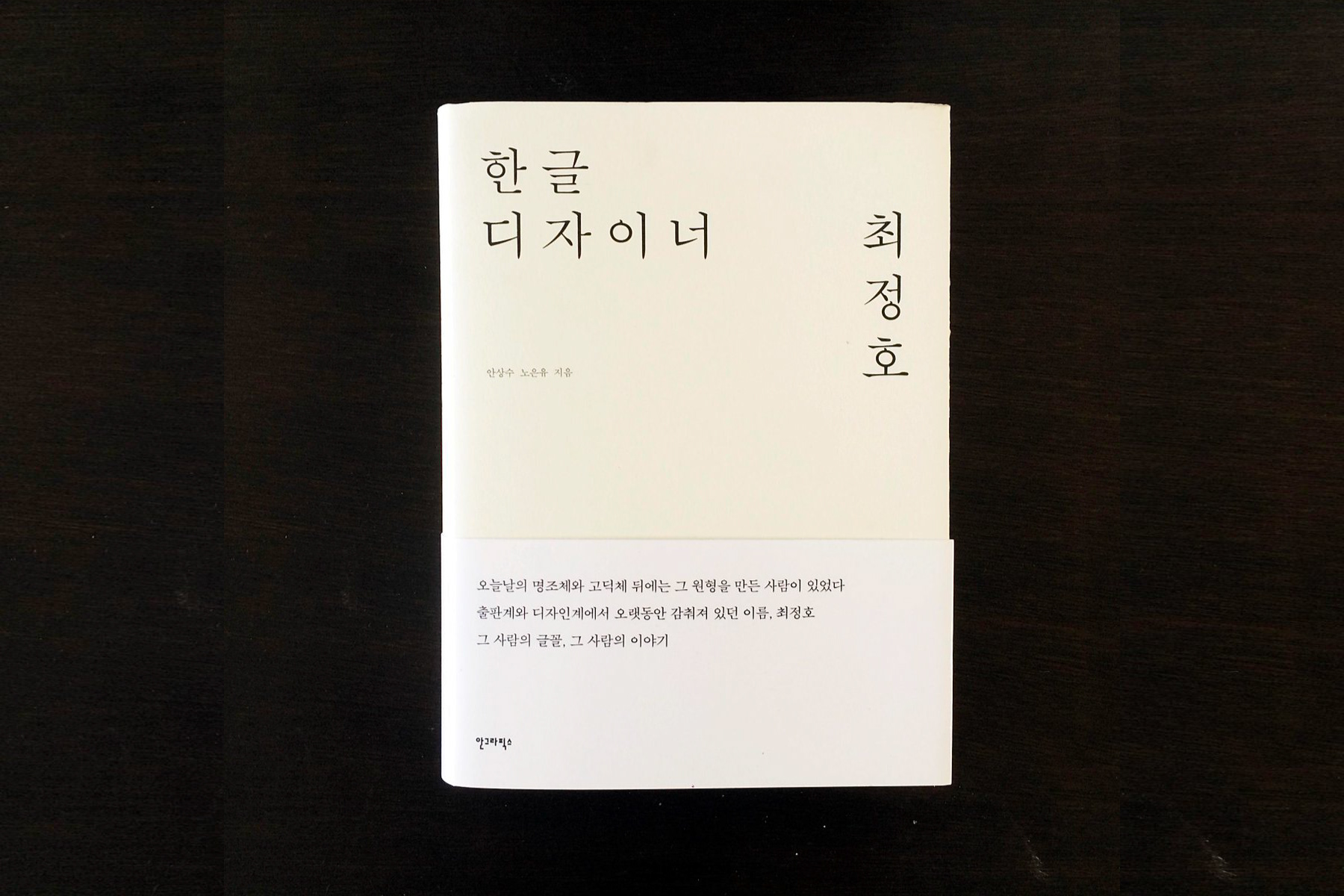
한글 디자이너 최정호​​​​​​​
Choi Jeong-ho’s Hangul Type Design, 2014
오늘날의 명조체와 고딕체의 원형을 설계한 1세대 한글디자이너 최정호 연구
Publication on Korea’s first generation Hangul type designer Choi Jeong-ho, responsible for the original designs of Myeongjo and Gothic.
글꼴에만 평생을 바친 최정호의 삶과 작업을 소개한 책이다.
먼저 ‘최정호의 삶’에서는 그의 삶을 하나하나 추적해 그를 기억하는 여러 사람의 목소리로 되돌아본다. 다음으로 ‘최정호의 한글꼴’에서 노은유의 박사논문을 바탕으로 최정호가 한국과 일본을 오가며 디자인한 수많은 글꼴을 체계적이고 논리적으로 분석했다. 또한 오늘날 명조체와 고딕체 계열 글꼴과 최정호가 디자인한 글꼴이 어떻게 이어져 왔는지 그 계보를 그렸다. 책의 마지막에는 최정호의 기고글, 작업 사진은 물론 그동안 공개된 적이 없는 글꼴의 원도(原圖)를 생생하게 보여주었다.
(207쪽 발췌) “글자란 사상이나 뜻을 전하는 도구이다. 특별한 조건이 붙지 않는 한, 읽는 이가 피로감을 느끼지 않아야 하고, 무엇보다 읽기 쉬워야 한다. 글을 읽으면서 독자는 글자에 담긴 사상이나 환경을 상상하고 이해하게 된다. 따라서 보기 좋고 안정된 글자는 심리적으로 읽기 좋다.”
This book is about Choi Jeong-ho, a man who devoted his life to letters and type.
First, “His Life” investigates his life and listens to the many people who knew him. Next, “The Letters of Choi Jeong-ho” is a systematic and logical examination of the typefaces designed by Choi Jeong-ho in both Korea and Japan. Also, a timeline of how Myeongjo and Gothic was continued with the typefaces designed by Choi. The book concludes with writings, photographs and never before seen original drawings of typefaces.
“Letters are tools to convey ideas and meaning. Without any extra requirements, readers should not be fatigued but read with ease. As they read, they take in and understand the ideas expressed and imagine the environment. Therefore, appealing and stable letters are psychologically easy to read.” (excerpt from page 207)